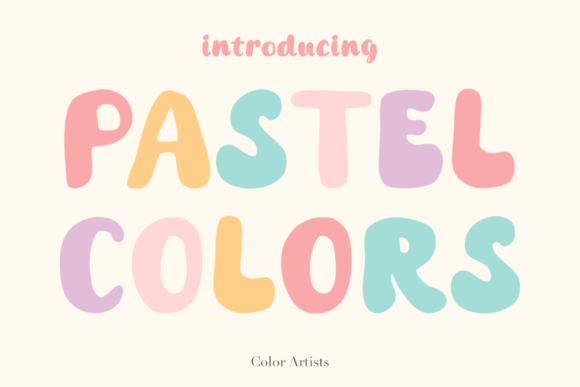
Pastel Colors
قد يكون العثور على عناصر التصميم المناسبة أمرًا صعبًا، ولكن Pastel Colors يقدم مجموعة استثنائية ترتقي بعملك على الفور.
تم تصميمه بدقة، ويوفر Pastel Colors متجهات نظيفة وطباعة سلسة وترخيصًا تجاريًا لراحة بالك.
سواء كنت تقوم بإنشاء منتجات الطباعة عند الطلب أو دعوات الزفاف أو رسومات وسائل التواصل الاجتماعي، فإن Pastel Colors هو الخيار المثالي.